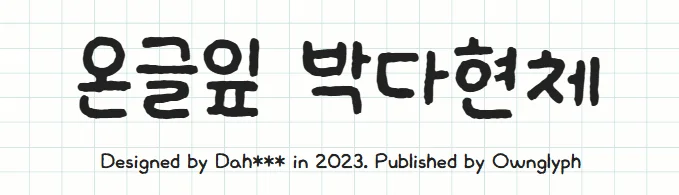
1. ์จ๊ธ์ ๋ฐ๋คํ์ฒด, ๋์ฒด ๋ญ๊ฐ์? ๐๏ธ
์จ๊ธ์ ๋ฐ๋คํ์ฒด(์๋ฌธ๋ช : Ownglyph PDH)๋ ๋์์ด๋ ๋ฐ๋คํ์ด ์์ ์ ์๊ธ์จ๋ฅผ ์ง์ ๋์งํธ ํฐํธ๋ก ๋ง๋ ์ํ์ ๋๋ค. (์ฃผ)๋ณด์ด์ ์์ค์ ์จ๊ธ์ ํ๋ซํผ์ ํตํด 2023๋ ๊ณต์ ๋ฐฐํฌ๋์์ผ๋ฉฐ, ๋๋ยท์ฐ๋๊ตฌ๋ฆยท๋์์ธ๋ฒ ์ด์ค ๋ฑ ๊ตญ๋ด ์ฃผ์ ๋ฌด๋ฃ ํฐํธ ํ๋ซํผ์ ๋ฑ๋ก๋์ด ์์ต๋๋ค.
| ํ๊ตญ์ด๋ช | ์จ๊ธ์ ๋ฐ๋คํ์ฒด |
| ์๋ฌธ๋ช | Ownglyph PDH |
| ์ ์์ | ๋ฐ๋คํ |
| ๋ฐฐํฌ์ฌ | (์ฃผ)๋ณด์ด์ ์์ค (์จ๊ธ์ ํ๋ซํผ) |
| ์ถ์ | 2023๋ |
2. ๊ธ์๊ฐ ๋ช ์๋ ๋ค์ด์์๊น? ๐ข
ํฐํธ๋ฅผ ์ค์ ๋ก ์จ๋ณด๋ฉด "์ด ๊ธ์๋ ์ ์์ง?"๋ผ๋ ์ํฉ์ด ์ข ์ข ์๊ธฐ์ฃ . ๋ฐ๋คํ์ฒด๋ ์ด๋ฐ ๊ฑฑ์ ์ด ๊ฑฐ์ ์์ต๋๋ค.
- ํ๊ธ 2,780์: ์ฌ๋งํ ์ผ์์ด๋ ๋ชจ๋ ํํ ๊ฐ๋ฅ
- ์๋ฌธ 52์: ๋์๋ฌธ์ A~Z ์ ์ฒด ํฌํจ
- ํน์๊ธฐํธ 125์: ๋ฌธ์ ์์ ์ ํ์ํ ๊ธฐํธ
- ์ซ์ 10์: 0~9 ๊ธฐ๋ณธ ์ซ์
๐ ์ผ์์ ์ธ ํ๊ตญ์ด ์ฝํ ์ธ ๋ฅผ ๋ง๋๋ ๋ฐ ํ์ํ ๊ธ์๋ ์ฌ์ค์ ๋ชจ๋ ํฌํจ๋์ด ์์ต๋๋ค.
3. ์ด๋ป๊ฒ ์๊ฒผ๋๋ฐ์? ๋์์ธ ํน์ง โจ
ํ๋ง๋๋ก ํํํ๋ฉด "๊ท์ฝ๊ณ ๋ฐ๋ปํ ์๊ธ์จ์ฒด"์ ๋๋ค. ๊ตฌ์ฒด์ ์ผ๋ก ์ดํด๋ณด๋ฉด ๋ค์๊ณผ ๊ฐ์ ๋งค๋ ฅ์ด ์์ต๋๋ค.
- ๋ฅ๊ทผ ํ: ์์ยท๋ชจ์ ๋ชจ๋ ๋ถ๋๋ฝ๊ฒ ์ฒ๋ฆฌ๋์ด ์์ด ์ฝ๋ ์ฌ๋์๊ฒ ํธ์ํ ์ธ์์ ์ค๋๋ค.
- ์์ฐ์ค๋ฌ์ด ํ์ฒด: ๊ธ์์ ๋๋ฎ์ด์ ๊ตต๊ธฐ ๋ณํ๊ฐ ์ค์ ํ์ผ๋ก ์ด ๊ฒ์ฒ๋ผ ์ด์ ์์ต๋๋ค.
- ์ ๋นํ ๋๊ป๊ฐ: ์ง๋์น๊ฒ ์์ง ์์ ์์ ๋ชฉ์ด๋ ํ์ดํ ์ฉ๋๋ก๋ ํ์ฉํ ์ ์์ต๋๋ค.
- ๊ฐ๋ ์ฑ ์ ์ง: ํ๋ฆผ์ฒด์ฒ๋ผ ์ฝ๊ธฐ ์ด๋ ต์ง ์๊ณ , ๊ท์ฌ์ฐ๋ฉด์๋ ๋๋ ทํ๊ฒ ์ฝํ๋๋ค.
4. ์ด๋์ ์ฐ๋ฉด ์ ์ด์ธ๋ฆด๊น? ์ถ์ฒ ์ฉ๋ ๐ก
์จ๊ธ์ ๋ฐ๋คํ์ฒด์ ๋ฐ๋ปํ ๊ฐ์ฑ์ ๋ฐํ์ผ๋ก ์ค์ ํ์ฉ์ ์ ๋ง๋ ์ฉ๋๋ฅผ ์ ๋ฆฌํ์ต๋๋ค.
- ๋ธ๋ก๊ทธ ์ธ๋ค์ผยท์นด๋๋ด์ค: ๊ฐ์ฑ ํ ์คํธ ์ด๋ฏธ์ง์ ๋ฑ!
- SNS ํผ๋ ๋์์ธ: ์ธ์คํ๊ทธ๋จ ๋ฑ์์ ๋ฐ๋ปํ ๋ถ์๊ธฐ ์ฐ์ถ
- ์ํธ์งยท๋ค์ด์ด๋ฆฌ ์ฝํ ์ธ : ์๋ ๋ก๊ทธ ๊ฐ์ฑ ๊ทน๋ํ
- ์คํฐ์ปคยท๊ตฟ์ฆ ๋์์ธ: ๋ฌธ๊ตฌ๋ฅ, ํฌ์คํฐ, MD ์ํ
- ์ ํ๋ธ ์ธ๋ค์ผยท์๋ง: ๋ฐ๊ณ ๊ท์ฌ์ด ์ฑ๋ ํค์ค๋งค๋
- ์ด๋ฆฐ์ด ๊ต์ก ์๋ฃ: ์น๊ทผํ๊ณ ๋ถ๋๋ฌ์ด ๋๋